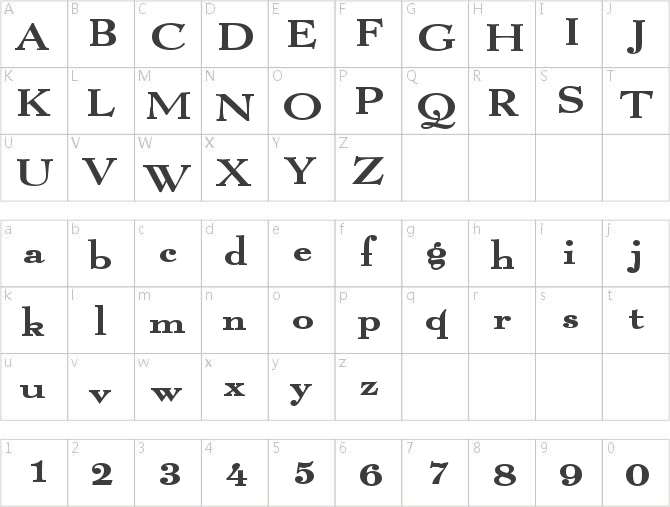
Luciano-Wide-Bold 詳情頁
Luciano-Wide-Bold字體字庫是一款讓人賞心悅目、百看不厭的英文字體,適合各類廣告和產(chǎn)品包裝設(shè)計(jì)應(yīng)用,字體大小0.06MB,格式為ttf字體,上傳用戶是17199970014,作者/版權(quán)方為未知